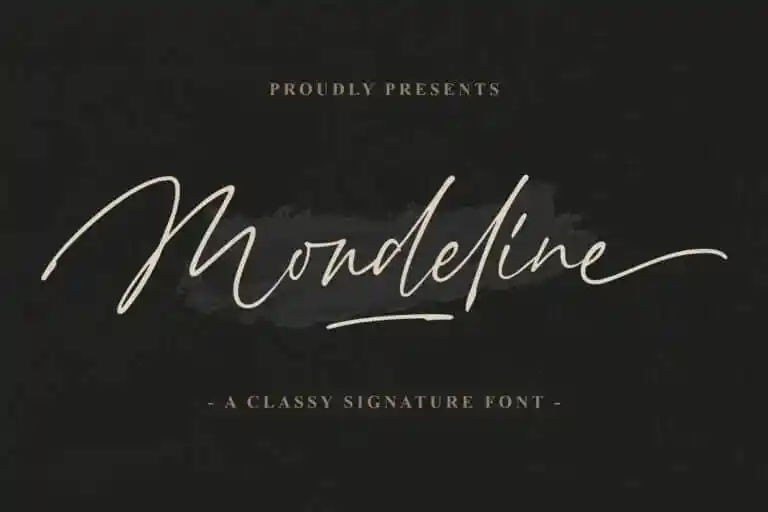
A Mondeline Script Font é uma elegante tipografia feita à mão que traz seu design para uma nova dimensão de elegância. Inspirada nas assinaturas e projetadas para dar um toque único a qualquer obra, esta fonte é perfeita para criar um estilo distintivo. Com sua arquitetura fluida e autêntica, ela oferece uma sensação sofisticada que vai tornar seus trabalhos mais interessantes e memoráveis. Mondeline é ideal tanto para criações de aparição quanto para o design de camisetas, arte em branco e preto, logotipos, adesivos personalizados ou qualquer outro uso onde um toque distintivo seja desejado. Essa fonte não apenas ressalta seu trabalho, mas também proporciona uma experiência visual única que vai destacá-lo entre a concorrência. Transforme sua comunicação em algo memorável com essa fonte de estilo script.